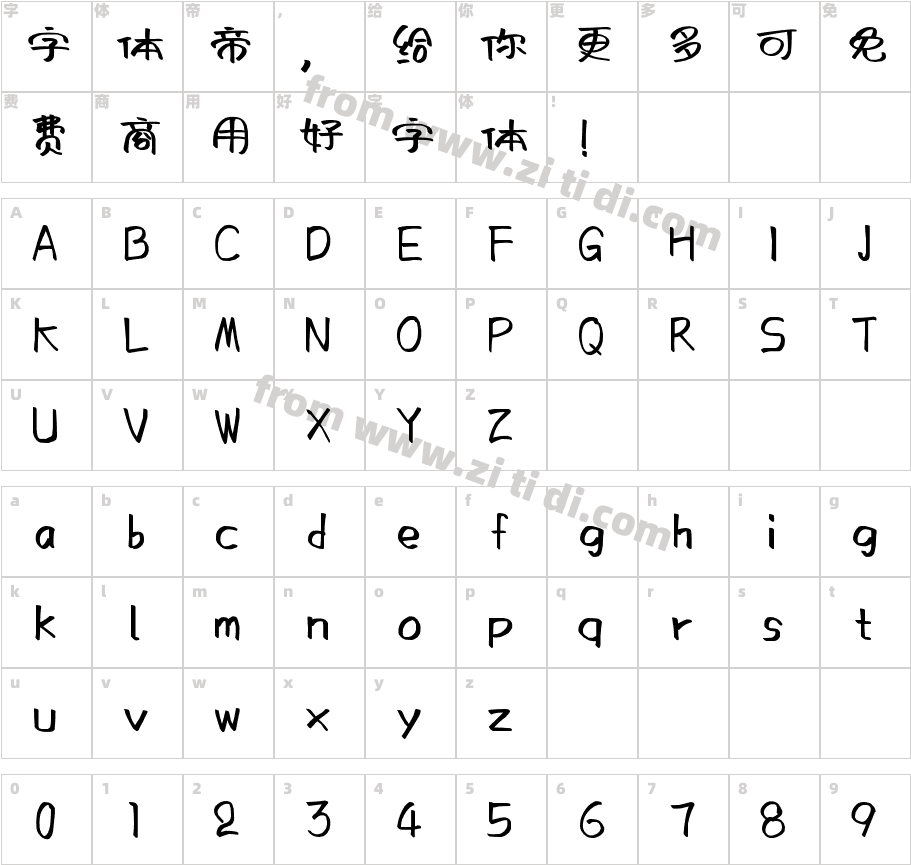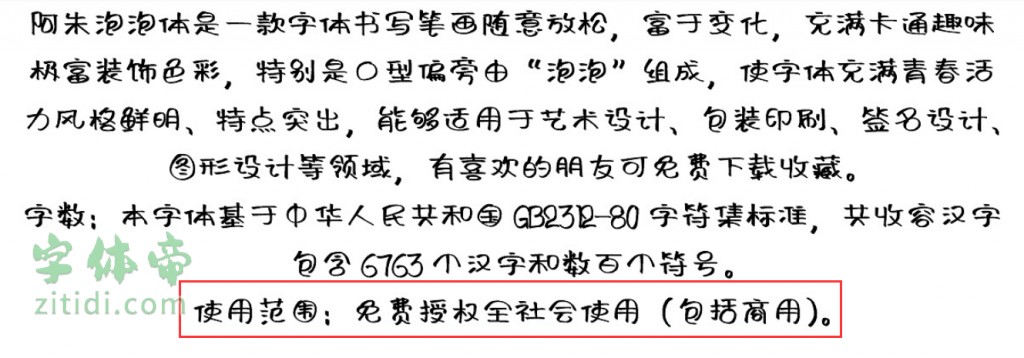
阿朱泡泡体发布于2019年的光棍节,这是一款字体书写笔画随意放松,富于变化,充满卡通趣味极富装饰色彩,特别是口型偏旁由“泡泡”组成,使字体充满青春活力风格鲜明,特点突出,能够适用于艺术设计、包装印刷、签名设计、图形设计等领域,有喜欢的朋友可免费下载收藏。
“阿朱泡泡体”是一款书写很新颖的字体,字体大方,适合各种设计作品使用!欢迎下载!